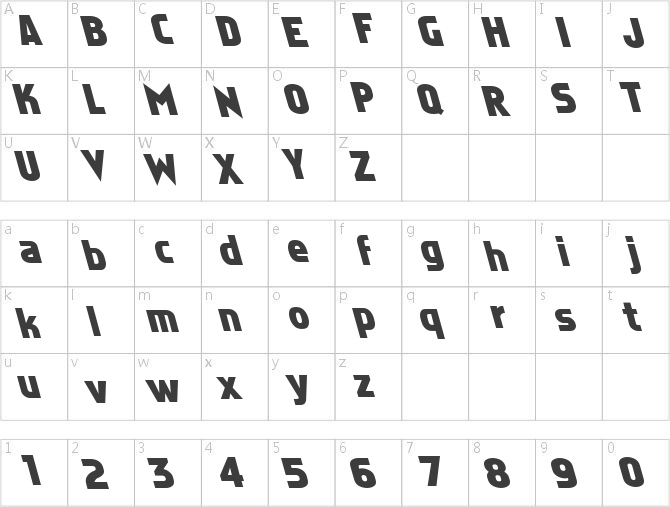
Faktos-LeftyCasual 詳情頁
字體名稱: Faktos-
Faktos-LeftyCasual
Faktos-LeftyCasual字體字庫是一款讓人賞心悅目、百看不厭的英文字體,適合各類廣告和產品包裝設計應用,字體大小0.05MB,格式為ttf字體,上傳用戶是KISEKI,作者/版權方為未知